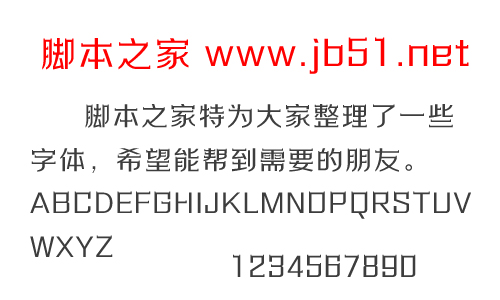
方正勁彩體系列字體基礎(chǔ)框架有點類似正統(tǒng)黑體,這款字平穩(wěn)中帶有動感,兩個角用作平行重心,充滿安穩(wěn)平靜,悠和舒暢的感覺,包 含8種不同粗細(xì),勁彩體系列字體設(shè)計靈感源于名勝公園內(nèi)一把很特別的休閑椅子靠背,椅子設(shè)計非常有創(chuàng)意,因此依靠椅子靠背的兩個角的特式,又抓到了創(chuàng)意靈感,因公園環(huán)境優(yōu)美,種滿了漂亮七彩的花朵,因此將它命名勁彩體,適合中青年男女品牌,旅行社,名酒品牌和健康產(chǎn)品的商業(yè)宣傳和包裝設(shè)計。歡迎喜歡此字體的朋友前來下載使用。